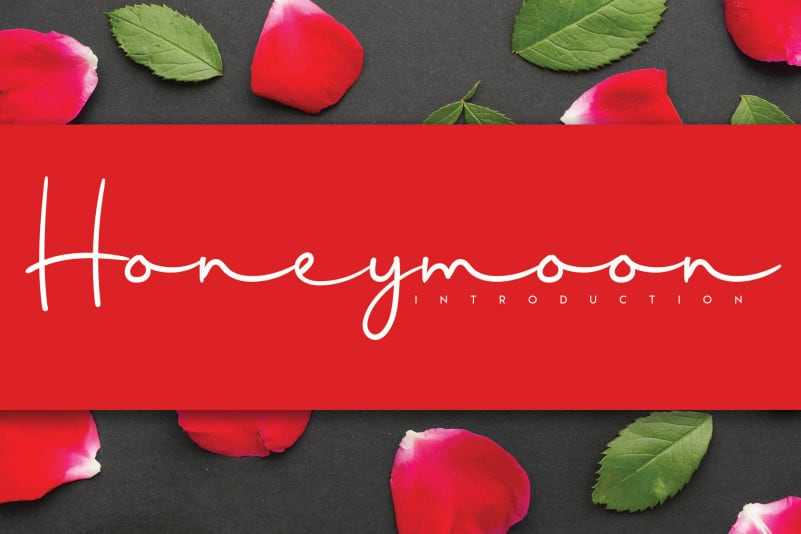
Honeymoon Handwritten Font – Download Grátis
A Honeymoon Handwritten Font é uma escolha única para aqueles que buscam uma experiência especial com uma fonte escrita à mão. Originada do designer andikastudio, essa fonte oferece um toque de criatividade e personalização sem igual. Cada caractere nesta fonte retrata momentos singulares e sentimentos profundos de maneira única e envolvente, proporcionando uma experiência visual distintiva em seu próximo projeto gráfico. Seja você designer de blogs pessoais ou de grandes marcas, a Honeymoon Handwritten Font está aqui para tornar suas criações ainda mais memoráveis e emocionantes através do toque suave e reconfortante de uma fonte escrita à mão.